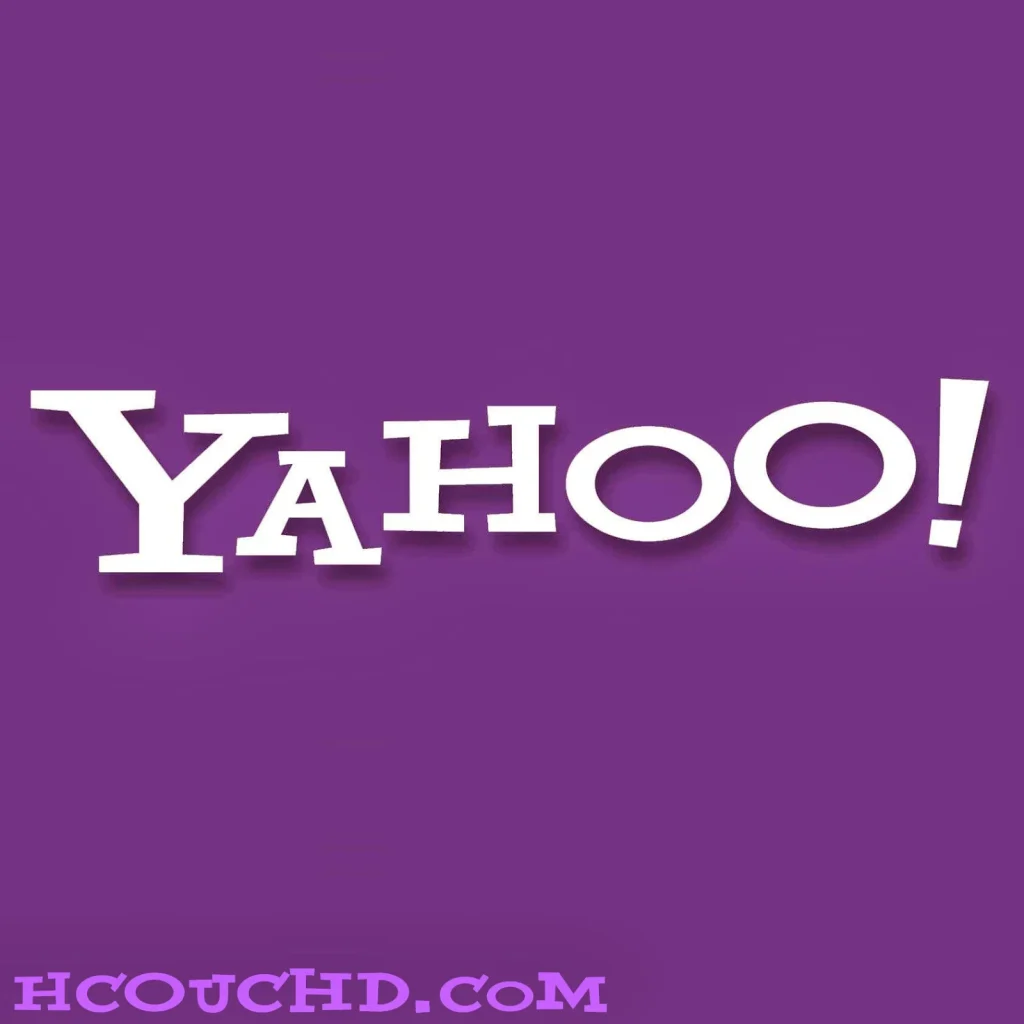
تحميل خط ياهو Yahoo مجانا { خطوط }
خط ياهو Yahoo لا يحتاج إلى وصف لأن الكثير يعرفون خدمات ياهو ، و يعتبر هذا الخط من أشهر الخطوط ، و هذا راجع إلى تصميمه متقن و شعبية شركة Yahoo العالمية ، يمكنك تحميل هذا خط من رابط أسفله …